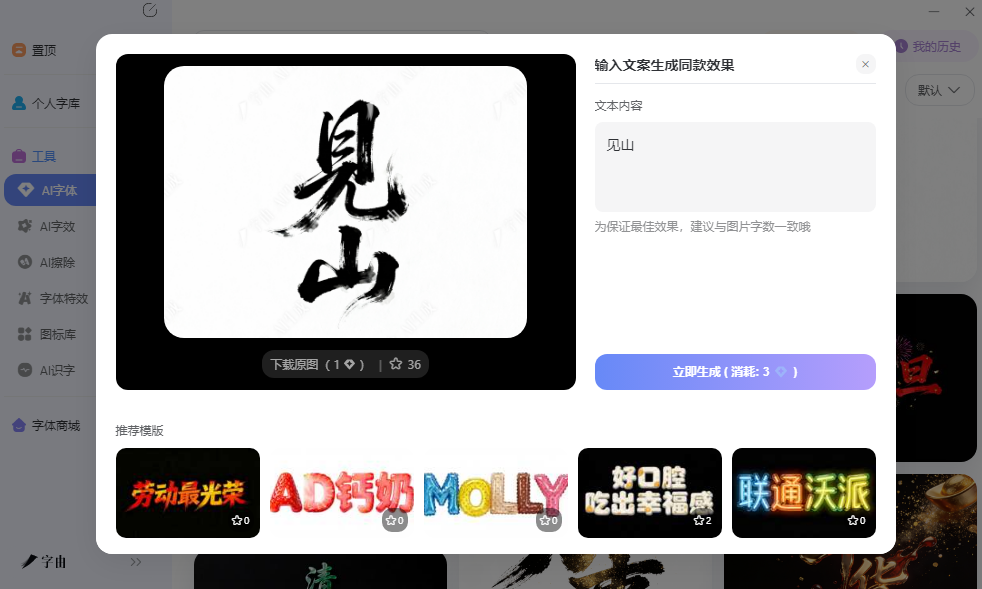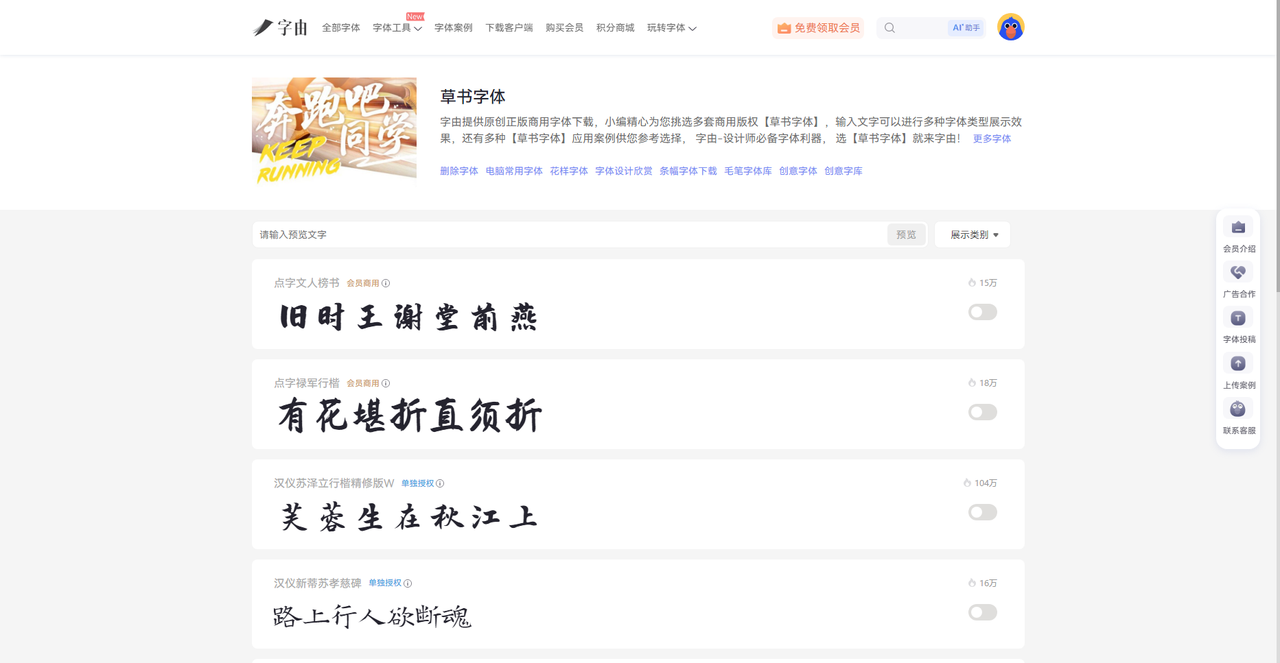
草书字体转换器推荐:在线生成毛笔草书
草书是最具艺术感的中文书法字体,笔画连绵、结构简省,狂草更是奔放不羁。但普通人要是想写成出一副好的草书实在是有点困难。如果想在设计中用草书做标题、做Logo、做海报,又没有书法功底怎么办?这时候在线草书字体转换器就是解决方案。你输入汉字,它自动转换成草书样式,可以下载图片或者复制粘贴。今天测评了5个草书转换工具,从字由的AI字效和专业草书字体,到多类型草书转换站,再到参数可调的生成器,覆盖了设计师和普通用户的不同需求。
字由作为综合性字体平台,在做草书这件事上有两条路径:一是AI字体功能里找草书风格的模板,直接生成带特效的草书艺术字图片;二是字由字体库里的会员商用草书字体,激活后在PS里用。
- 路径一:AI字体生成草书特效图
打开字由客户端,进入“AI工具”下的“AI字体”。在模板库里搜索关键词“草书”“行草”“狂草”“书法”,或者直接浏览“国潮风”“手写书法”等分类,你会找到不少带有草书笔意的模板。这些模板不只是把文字转换成草书字形,还配好了墨迹纹理、飞白效果、宣纸背景等元素,生成出来的图片可以直接用于海报标题、封面、品牌主视觉。
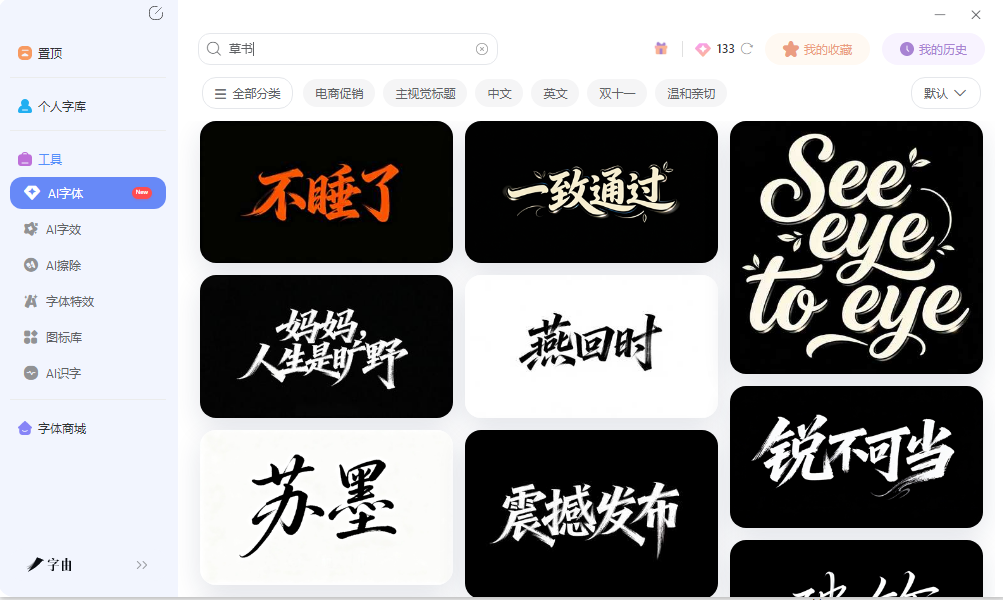
选择一款喜欢的草书风格模板,点击“做同款”,在右侧输入框里输入你的文案——可以是品牌名“云水间”,也可以是一句诗词“大江东去”。点击“立即生成”,大约20到30秒后,系统就会输出一张高清草书艺术字图片。
- 路径二:客户端选草书字体,激活后直接使用
字由的字体库里专门设有“草书字体”分类。打开字由客户端,在左侧筛选栏里找到“字体类型”,勾选“书法体”,然后在在搜索框输入“草书”。你会看到字由整理的多款草书字体,例如“点字文人榜书”(会员商用)、“点字禄军行楷”(会员商用,行楷介于行书和草书之间)、“汉仪苏泽立行楷精修版”(单独授权)、“汉仪新蒂苏孝慈碑”(单独授权)等。每款字体都标明了授权类型和使用热度,热度高的说明被大量设计师使用过。
字由还提供了客户端、网页版、小程序等多个入口,随时随地浏览和激活字体。草书字体库覆盖了从传统章草、今草到现代创意草书的多种风格,无论你是要庄重的碑刻草书,还是狂放的当代草书,都能找到对应资源。
2、繁体字在线转换
第二个网站是繁体字在线转换旗下的“草书字体转换器”。这个站专门做各种书法字体的在线转换,草书是其中一个重要分类。打开页面,你会发现它把草书分成了多个子类型:转草字、转行草字、转今草字、转草草字、转毛体。还提供了章草字体转换器、行草字体转换器、狂草字体转换器等独立入口。
操作方法很简单:在上方输入框输入你想要转换的汉字或句子,点击“转换为草书字体”按钮,下方就会展示出转换后的草书效果。转换结果以图片形式呈现,可以保存或截图使用。网站还附带了详细的草书字体介绍,讲解了草书的起源(始于汉初)、演变过程(章草→今草→狂草)、艺术特点(化繁为简、点画相连、使转交替等)。这些知识对于理解不同草书风格的区别很有帮助。
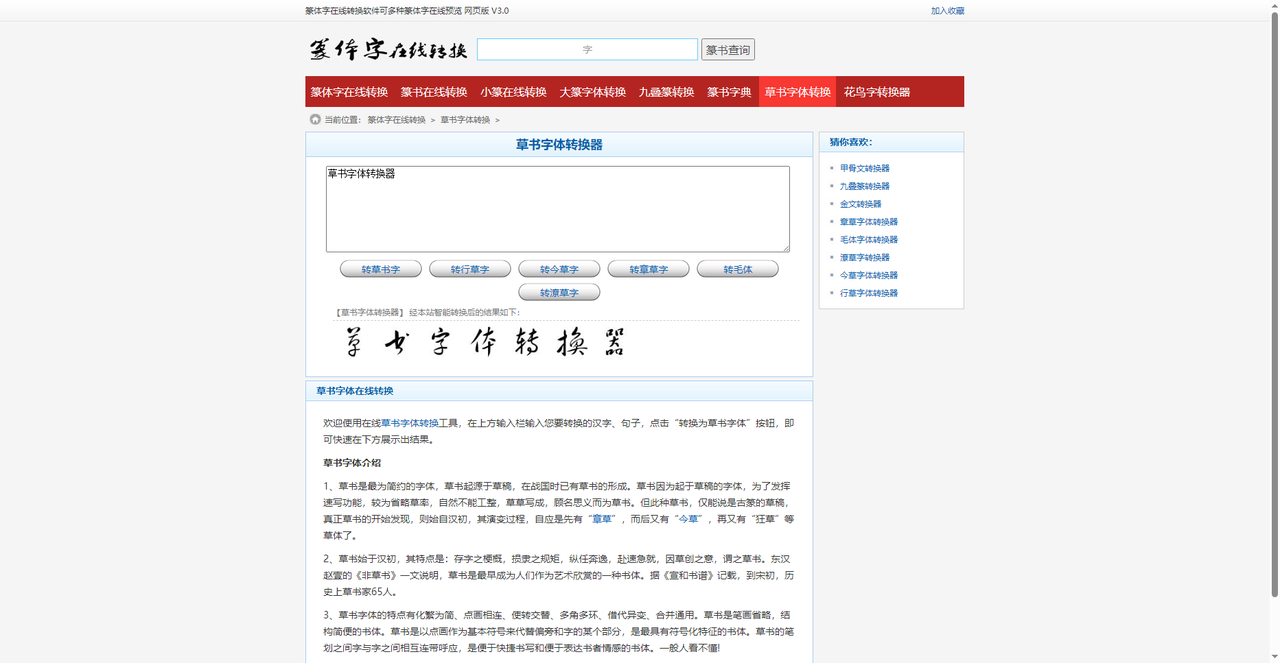
3、草书字体在线生成器
第三个工具是草书字体在线生成器(截图中的第三张图)。它提供了一种更灵活的方式:用户可以在线选择具体的草书字体,调整字体大小、颜色、背景,然后生成图片。打开页面,在“选择字体”下拉菜单里,可以看到“黎凡草书繁体”等选项。下方可以调节字体大小(默认66px)、字体颜色(支持十六进制色值)、背景颜色(默认白色),还提供了“开启背景透明”的选项。输入要转换的文字后,点击“点击开始生成”按钮,就能得到一张草书图片。
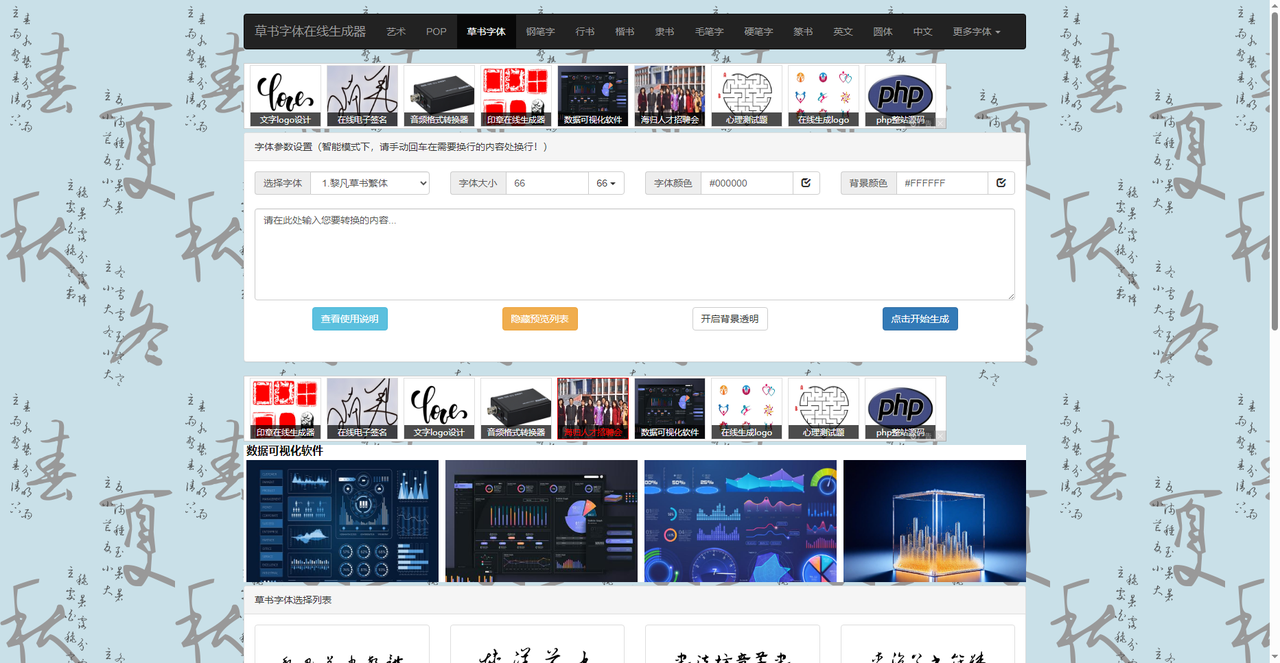
4、书法字体在线转换
第四个网站是一个书法字体在线转换工具(截图中的第四张图)。它提供了“叶根友刀锋黑草”等知名书法字体。叶根友是国内知名的书法字体设计师,其刀锋系列字体以其独特的锋利笔画和现代感广受欢迎。刀锋黑草兼具草书的连笔和黑体的力量感,很适合做标题和Logo。这个站还提供了行书字体转换器、毛笔书法在线转换等工具,是一个综合性的书法字体转换平台。如果你喜欢叶根友系列的草书风格,可以在这里快速预览效果,然后再决定是否购买正版。
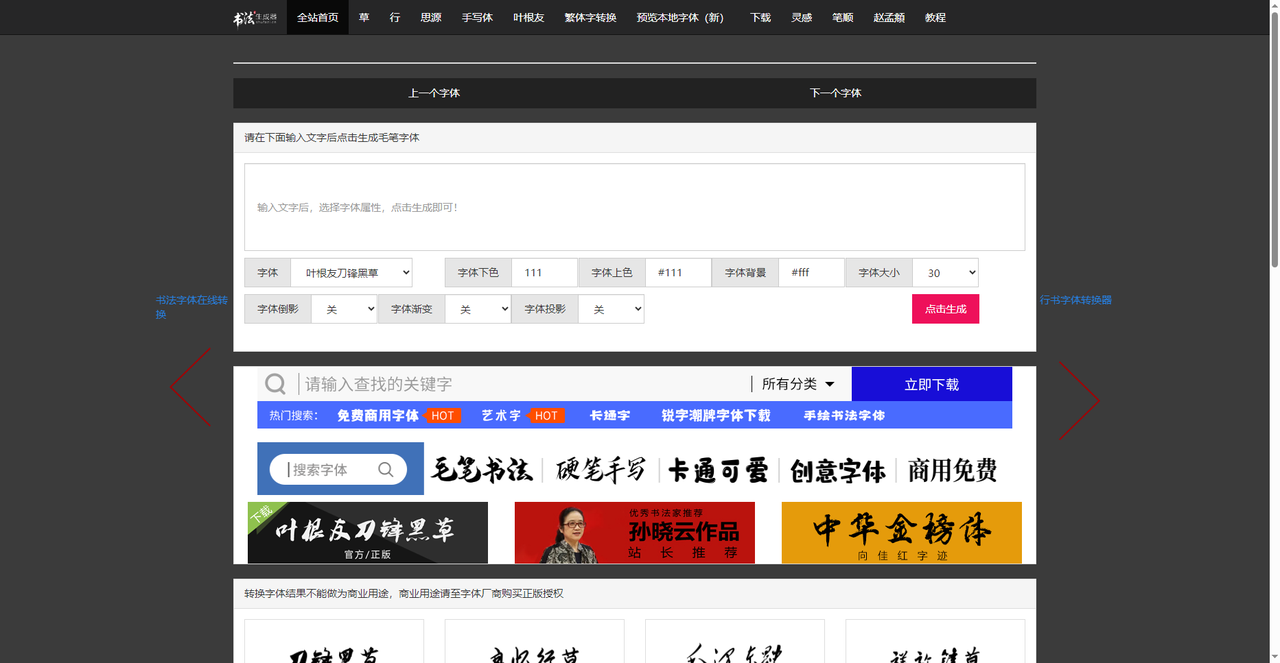
5、字体家
第五个网站是字体家。它是一个大型中文字体平台,收录了13861款中文字体,字体家的特点是字体资源极其丰富,不仅有草书,还有黑体、宋体、楷体、书法体、创意体等几乎所有类型。每款字体都标注了来源厂商和授权类型(免费商用或付费),并提供下载链接或购买入口。如果你想一站式浏览大量草书字体,对比不同风格,字体家是一个很好的资源站。它还提供了“AI造字”和“字体转换器”功能,可以在线生成效果。缺点是导航稍显复杂,需要花时间探索。
五个草书字体转换工具,各有侧重。字由最适合设计师的专业工作流,AI字体直接生成草书特效图,会员商用草书字体激活后在PS里随便用,覆盖了临时出图和长期使用的两种场景;书法字体在线转换支持叶根友刀锋黑草等热门字体,适合预览流行草书效果;字体家拥有海量中文字体库,草书分类齐全,适合批量筛选和对比。输入文字,选择喜欢的草书风格,几秒钟就能看到飘逸的毛笔草书效果。不管你是做海报还是发朋友圈,总有一个工具能帮到你。